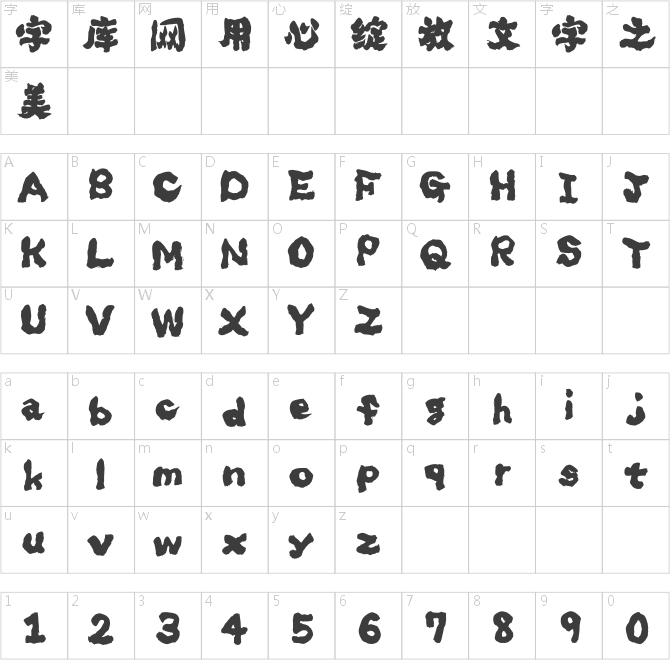
字体名称: 方正白舟魂心体
方正白舟魂心体
方正白舟魂心体是一款倾注全身力量书写的字体,由惯用右手的书法家使用左手书写制作的,用笔震颤曲折,仿佛一条蜿蜒的河流,在笔锋处留有点墨,更显深邃悠远。方正白舟魂心体笔画极粗,结构有紧有放、坚实有力,如果在大字号的标题字场合下使用,能让人切实感受到那种充满人情味的力量感。这款字体的原始字符由藤本惠书写创作而成。